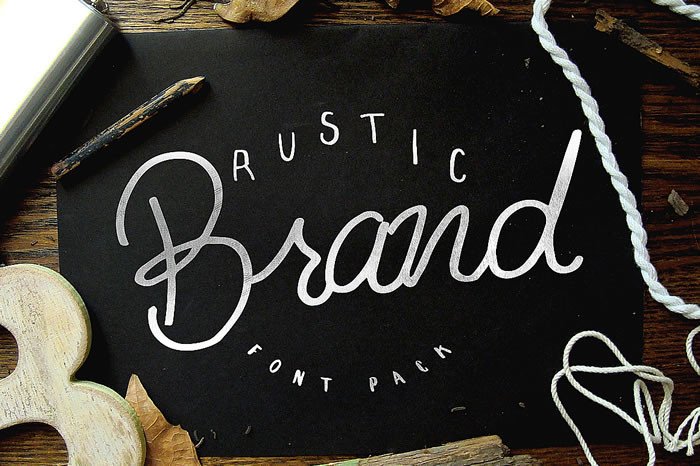
Rustic Brand
適切なデザイン要素を見つけるのは難しい場合がありますが、Rustic Brandは作品を即座に引き立てる優れたコレクションを提供します。
精密に作られたRustic Brandは、クリーンなベクター、滑らかなタイポグラフィ、そして安心のための商用ライセンスを提供します。
POD(オンデマンド印刷)製品、結婚式の招待状、またはソーシャルメディアのグラフィックを作成している場合でも、Rustic Brandは理想的です。